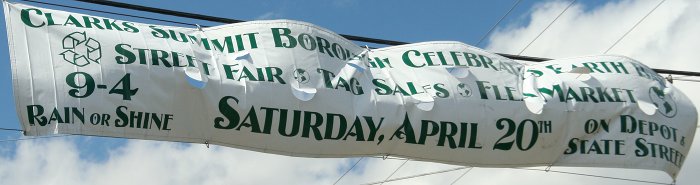
Planen-Gestaltung auf Anhänger
zum ersten Mal in meinem Leben habe ich den Auftrag bekommen eine Plane für einen Anhänger zu gestalten.
Ich habe noch nie eine schöne Plane auf einem Anhänger gesehen, der irgendwo herumsteht, damit Autofahrer ihn anschauen. Meistens zwei Schlagwörter und eine Telefonnummer gesetzt in einer verzerrten fetten Helvetica.
Nun sitze ich gerade dran und denke mir, dass diese Art der Werbung für Anhänger-Planen-Gestaltung wohl die einzige ist, die funktioniert? Diese Werbeform ist mir eigentlich völlig suspekt, weil ich niemals so einem Ding Aufmerksamkeit schenken würde oder geschweige denn die Telefonnummer notieren würde.
Nun sitze ich hier frustriert und weiß nicht was ich tun soll. Die typografischen Ideale muss ich wohl aufgeben, damit dieser Anhänger überhaupt funktionieren kann?
Ich weiß nicht wie ich mit meinem Corporate Design damit umgehen soll oder mit Schriftgrößen und Textabständen oder dem Logo. Das Logo weglassen und nur die Telefonnummer plus Schlagwörtern?
PS: Gibt es Studien über die Wirksamkeit dieser Anhänger-Beschriftungen neben einer befahrenen Landstraße?
Zumindest in Hamburg würdest Du Dir den Hass aller Parkplatzsuchenden zuziehen. Andererseits gibt es hier viel Werbung (die Stadt finanziert so die Stadtmöblierung) am Straßenrand bis hin zur Verkehrsgefährdung. Da es also alle machen, scheint ein gewisser Effekt vorhanden zu sein...
Ernsthaft: Telefonnummer halte ich auch immer für recht sinnfrei – es sei denn es ist so eine Taxinummer wie 55555, die sich schnell einprägt.
Der Absender sollte halt schnell und klar erkennbar sein und vielleicht noch ein kurzer, knackiger Slogan und gut ...
Ich habe ja den Zweck des Stranges noch nicht ganz verstanden. Heißt die Fragestellung tatsächlich »Soll ich mir wirklich Mühe geben für diesen Job oder ist eh’ alles Wurst?«
Was man aus der Plane machen kann, hängt natürlich immer davon ab, was da beworben werden soll, aber man kann das immer besser oder schlechter machen.
Ich habe mit Planenwerbung im öffentlichen Raum (eher an Gebäuden als an Fahrzeugen) eigentlich sehr gute Erfahrungen gemacht, was die bewußte Wahrnehmung durch potentielle Kunden angeht, jedenfalls deutlich bessere als mit Zeitungsanzeigen und dergleichen. Die Telephonnummer halte ich für sehr wichtig, aber nicht unbedingt als tragendes Element der Gestaltung.
Ich habe mal eine Anhänger für eine Fahrschule gestaltet. Kräftige Grundfarbe mit weißer Stadtsilhouette, dazu über der Silhouette das Logo, den Slogan und die Webadresse, ebenfalls in weiß. Das sah plakativ und trotzdem hochwertig aus. Und hatte ein tolle Signalwirkung – sowohl im Straßenverkehr als auch wenn der Anhänger auf dem Grundstück der Fahrschule als Blickfang stand.
Man kann aus allem etwas machen – einfach die Herausforderung annehmen und loslegen!  :-)
Bei solchen Draußeneinsätzen sollte man m.E. auch im Auge behalten, was Wind und Wetter aus unseren schönen Gestaltungen machen können. Ein Beispiel:
Die Intention des Gestalters dürfte klar sein: die Schrift auf dem Banner zum Umwelttag besonders blättrig, rankig, eben grün wirken. Aber auf einem hoch über der Straße durch den Wind gebeutelten Banner wäre eine schlichtere Schrift wahrscheinlich besser gewesen.
P.S. Ich hatte das Banner ursprünglich fotografiert, weil mich die »slashed Ohs« irritiert hatten. Kennt jemand zufälligerweise die Schrift?
(Haben wir die nicht schon mal gesucht? Kommt mir irgendwie bekannt vor …)
Nun ja, das ist eine von vielen Möglichkeiten, aber nicht die einzige. Zunächst müsste man wissen, wie groß der Anhänger ist, was denn überhaupt beworben werden soll (ein Produkt? eine Telefonnummer? reine Imagewerbung? eine Aktion? …?), ist eher Nah- oder doch Fernwirkung erzielbar und erwünscht und so weiter und so fort.
kann natürlich eine großartige Herangehensweise sein, wenn man sich möglichst bedeckt halten möchte, wer denn der Absender der Werbung ist. Ob das zielführend ist, steht wieder auf einem anderen Blatt.
Es geht um ein kleines Unternehmen, das alles rund ums Fenster vertreibt: Plissees, Jalousien, Insektenschutz und solche Dinge. Insgesamt sind es 5 Schlagwörter, von denen zwei Schlagwörter 80% des Umsatzes ausmachen.
Glatter hab ich’s nicht.
Ich weiss nicht ob die gesuchte dabei ist aber hier gibts einige dieser 'Ohs'
Aha! Verschiedene Alternativbuchstaben der Desire enthalten gleich mehrere Besonderheiten dieser Schrift. Nicht nur die O-Bippusse, sondern z.B. auch die A-Querstriche u.a.